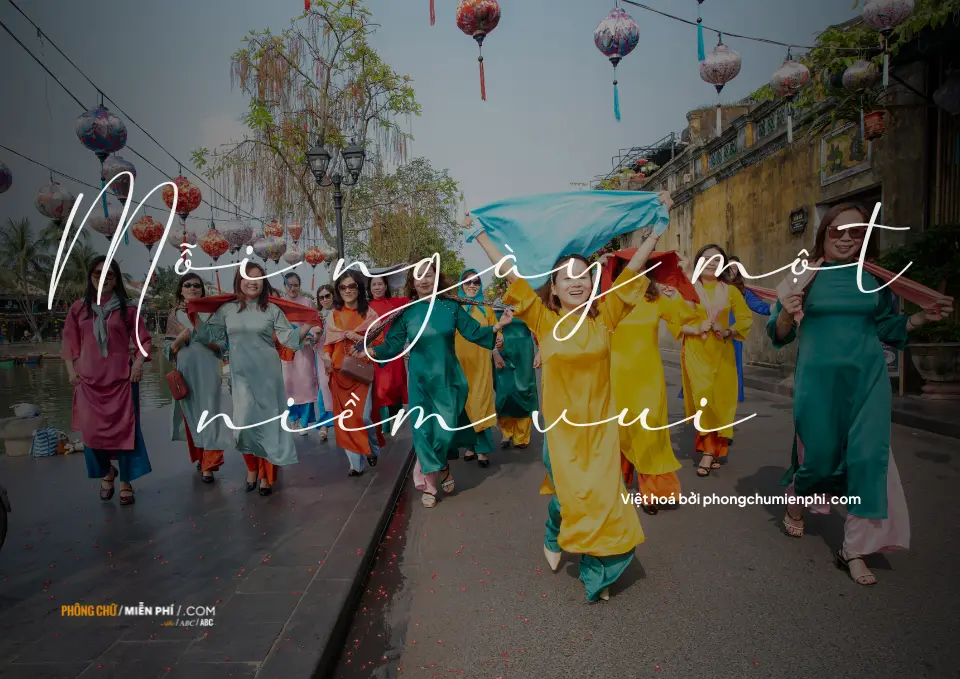
Tên font: Font Việt hoá Cherolina
PCMP Cherolina là một phông chữ Regular TrueType mang phong cách viết tay mềm mại và tự nhiên. Các nét chữ thanh thoát, uyển chuyển giúp font này trở thành lựa chọn lý tưởng cho những thiết kế cần sự lãng mạn, tinh tế và gần gũi. Bạn có thể sử dụng Cherolina cho nhiều mục đích khác nhau như: thiết kế thiệp cưới, thiệp mời sự kiện, logo thương hiệu, tiêu đề tạp chí, bài đăng mạng xã hội hay các dự án mang dấu ấn cá nhân.
Ngoài ra, bộ ký tự đầy đủ của PCMP Cherolina giúp bạn dễ dàng áp dụng vào nhiều ý tưởng sáng tạo khác nhau.